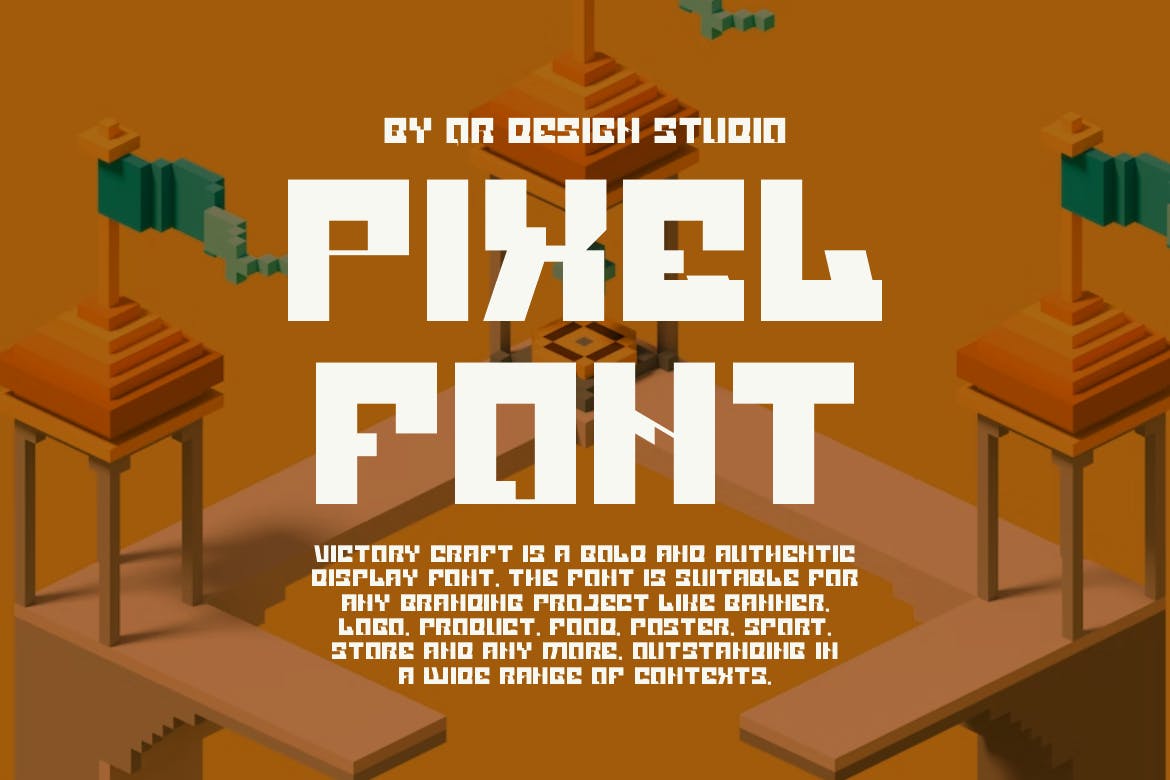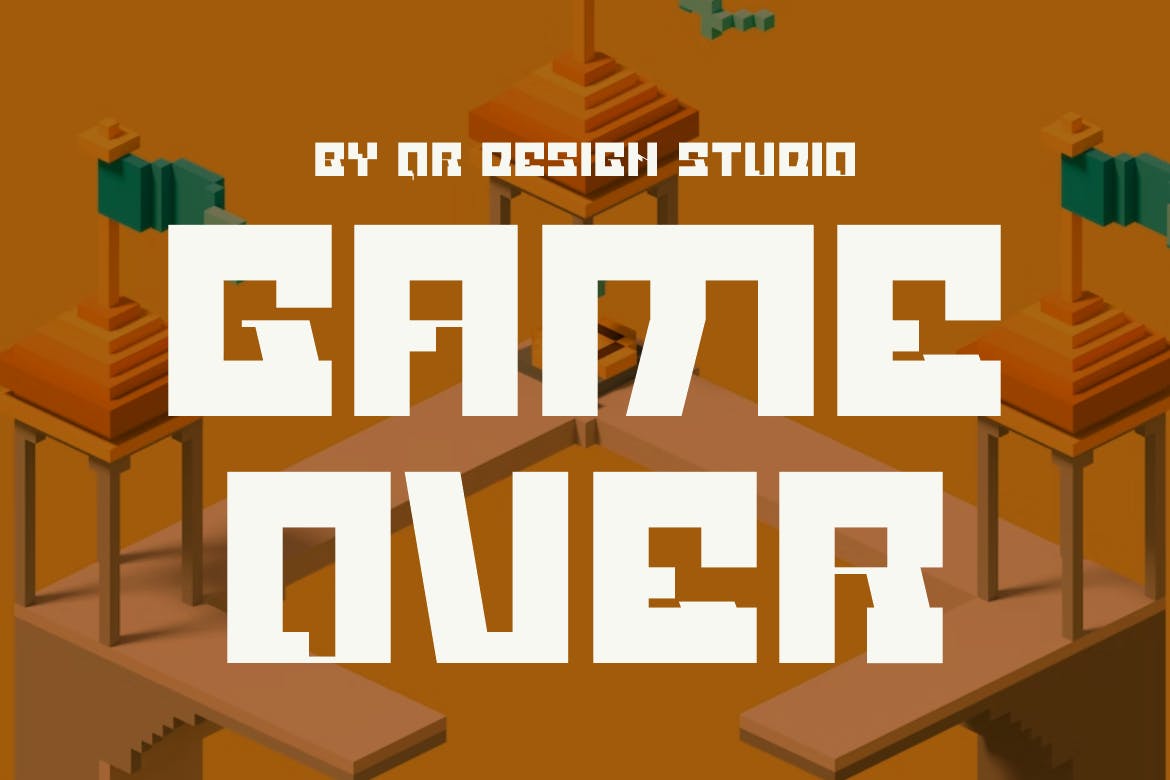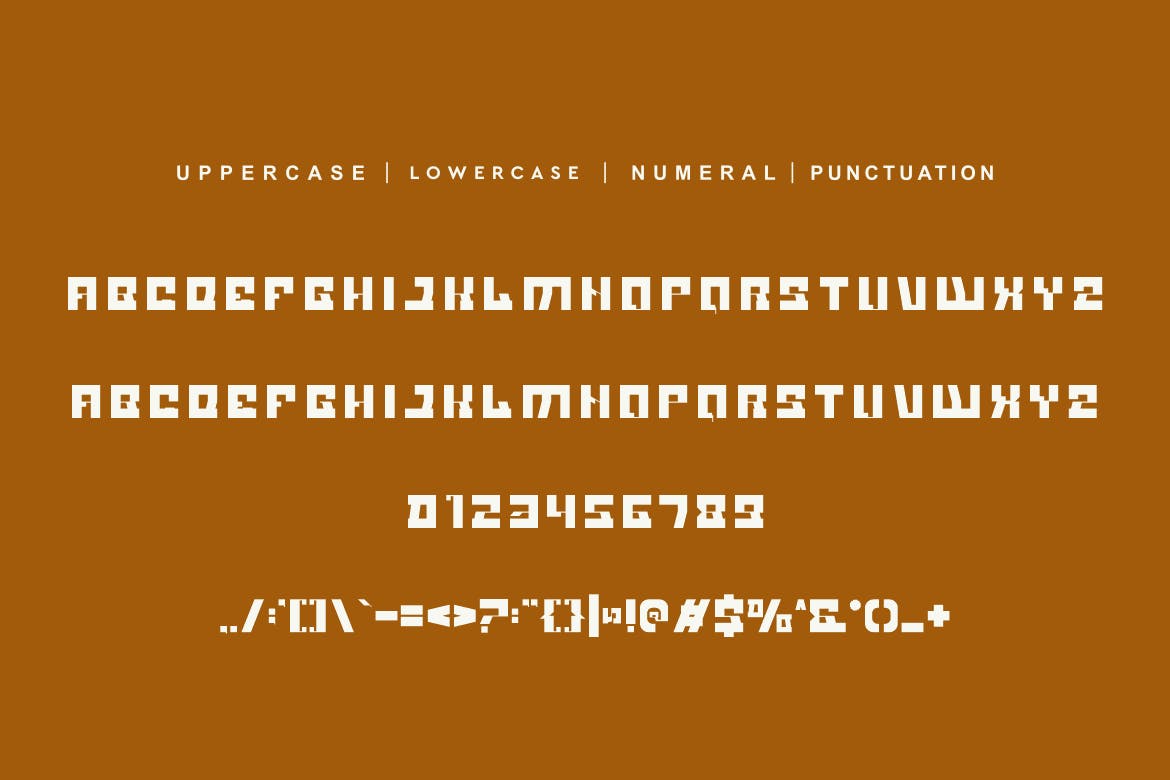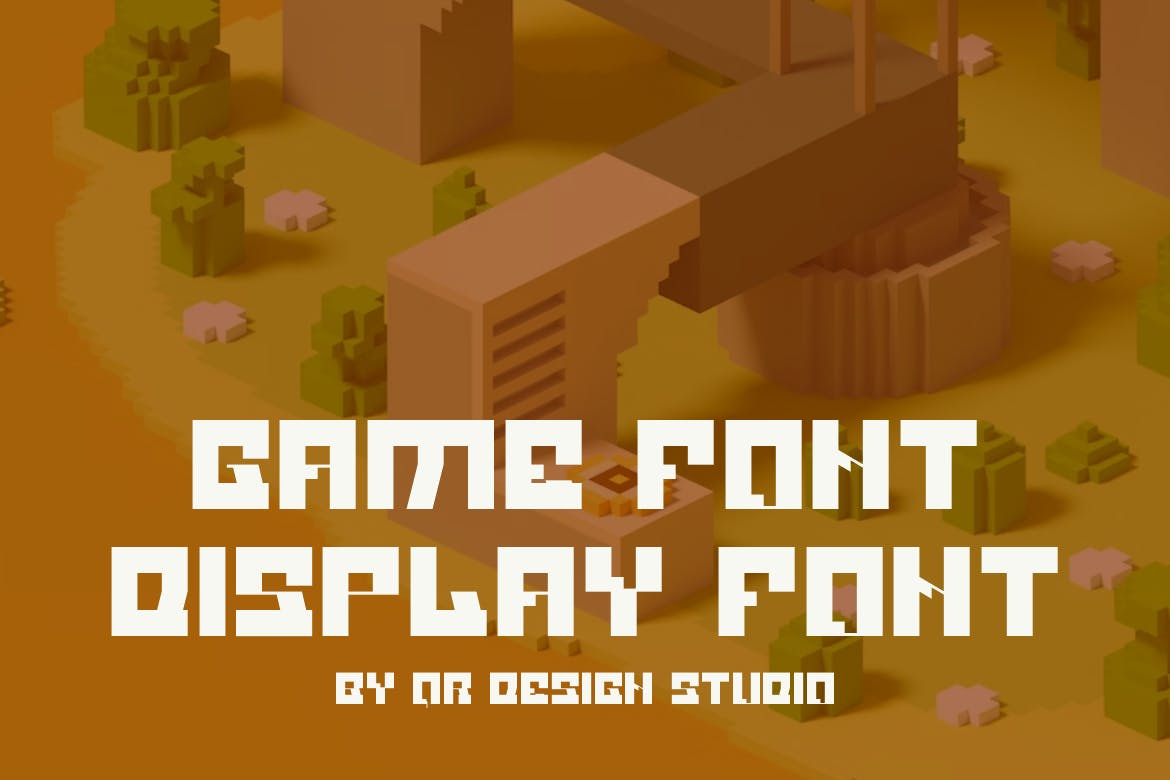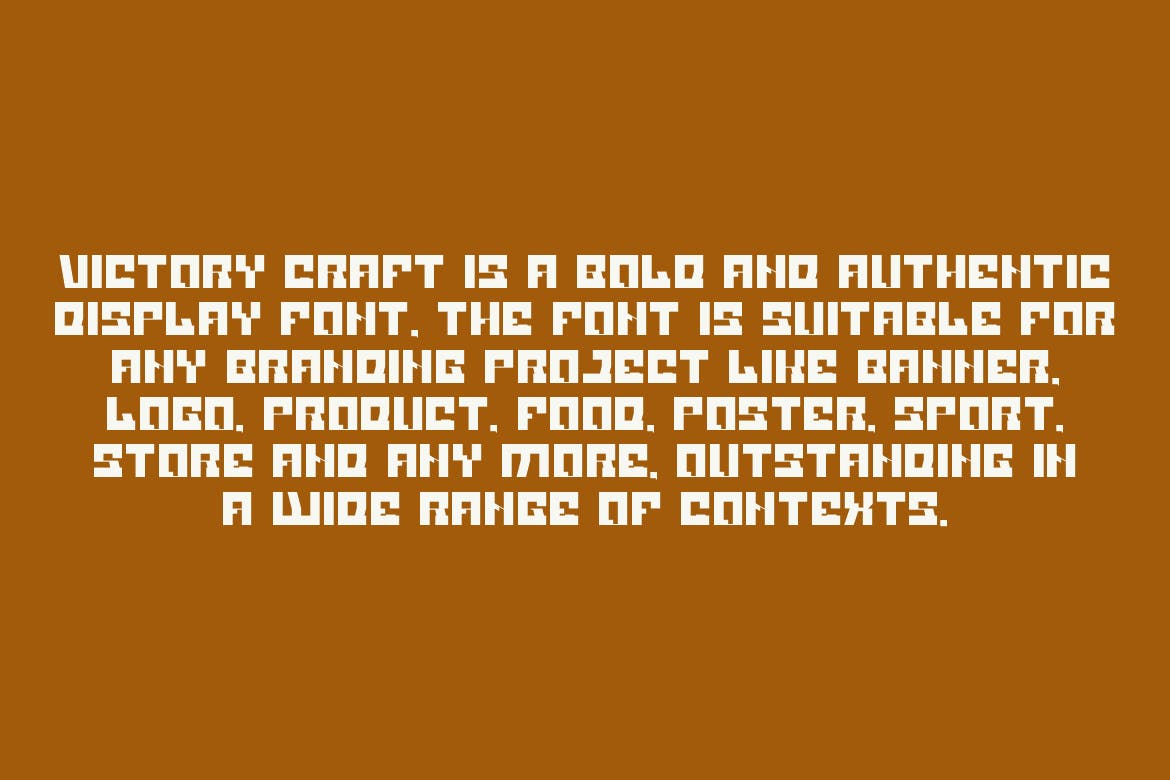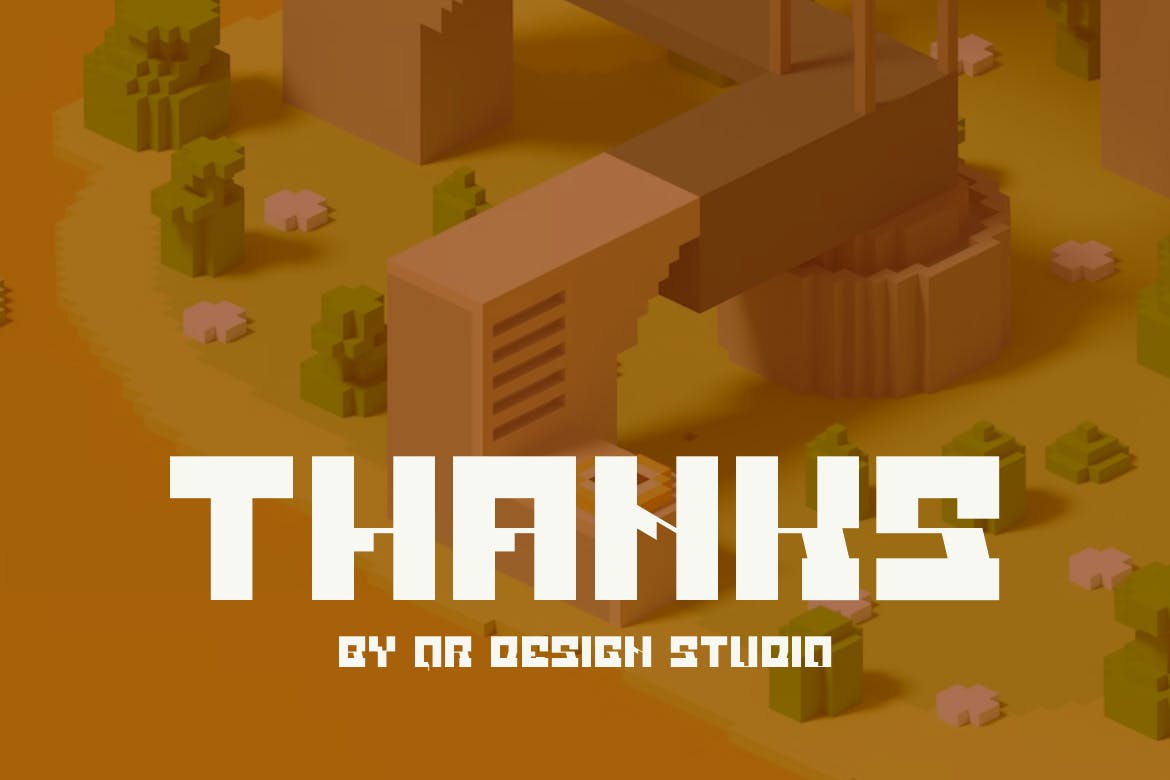
Victory Craft Pixel Game Font
فونت Victory Craft یک انتخاب ایده‌آل برای طراحی‌های گرافیکی و برندینگ است.
فونت Victory Craft - Pixel & Game یک فونت نمایشی برجسته و اصیل است. این فونت برای هر پروژه برندینگ از جمله بازی‌ها، پوسترها، لوگوها، ورزش و بسیاری موارد دیگر مناسب است. در زمینه‌های مختلف عملکرد فوق‌العاده‌ای دارد.